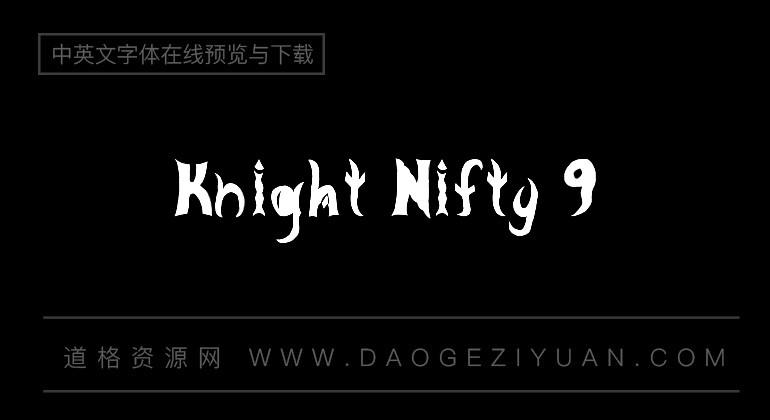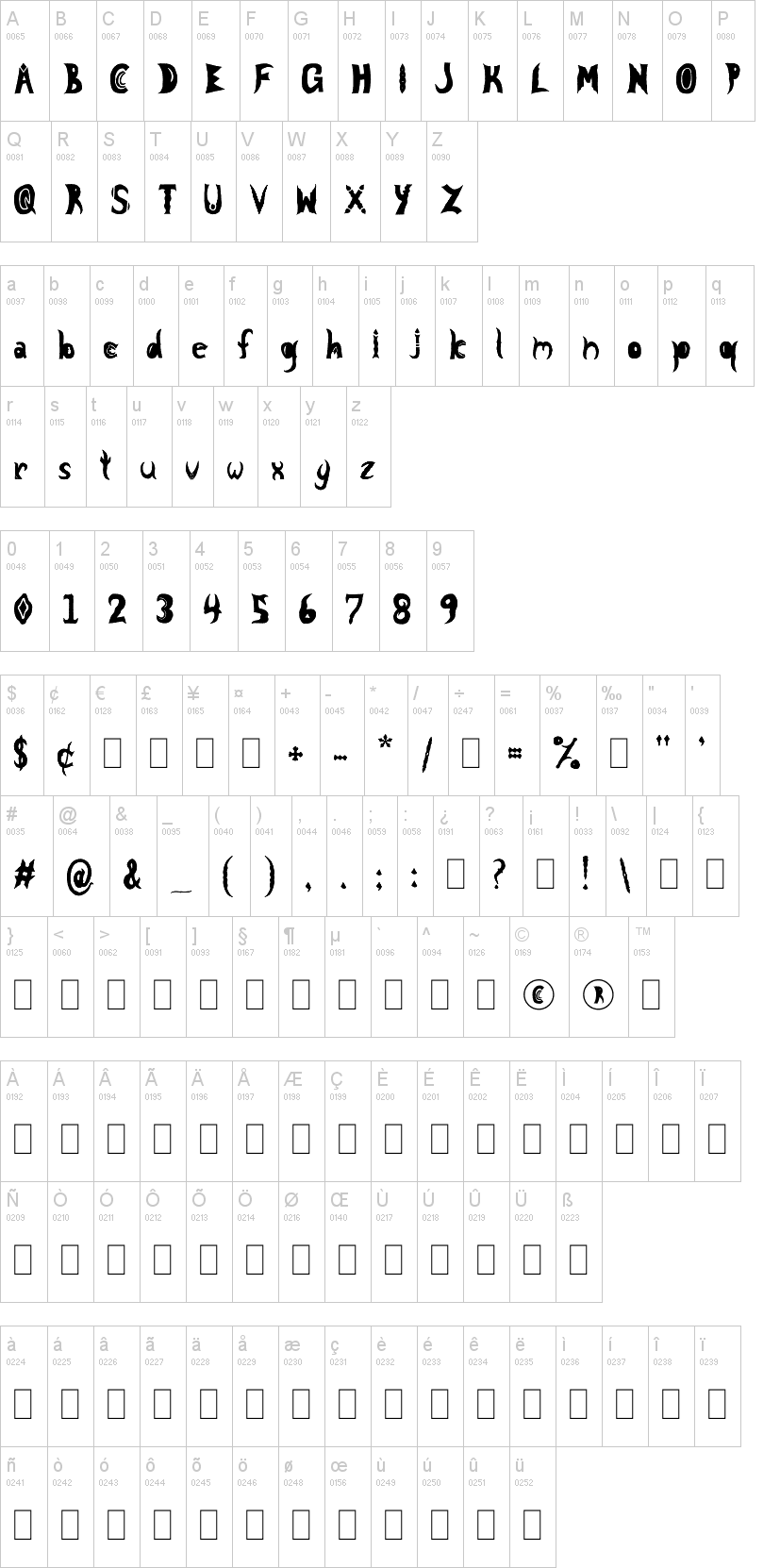
Knight Nifty 9
Knight Nifty 9 是一款新推出的字体,它拥有独特的设计,可以让您的文本看起来更加清晰和易读。它有一种活泼的感觉,可以让您的文字更加有趣。它还有一种现代感,可以让您的文字看起来更有活力。它的字体设计也更加简洁,可以让您的文字更加精练。此外,它还有一种特殊的“粗体”效果,可以让您的文字看起来更有力量。
Knight Nifty 9是一款非常不错的手写艺术字体,具有很好的视觉感,适合于文化类的宣传设计、商业类品牌的广告和产品包装设计以及个性化文字排版等较多场景。
Knight Nifty 9字符映射图